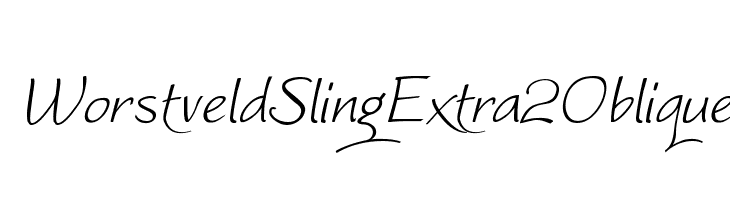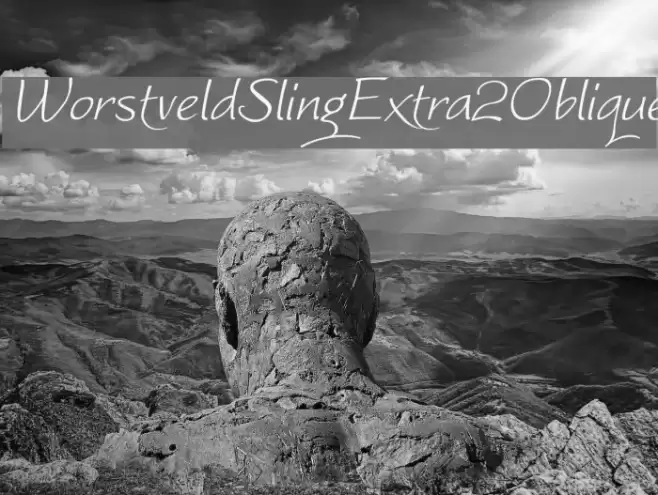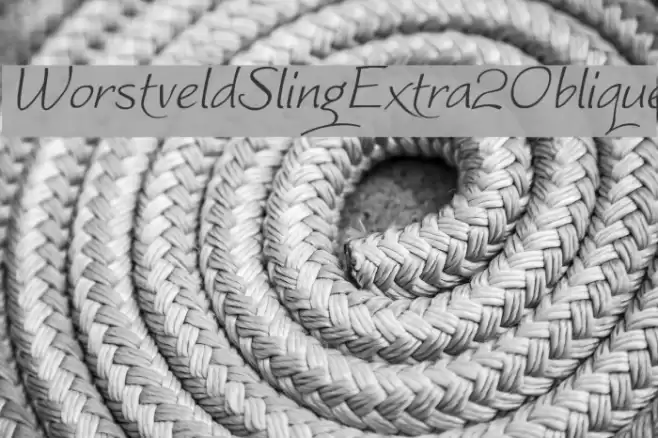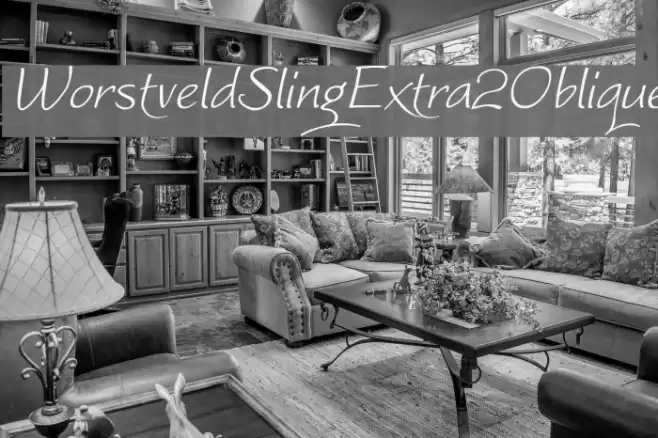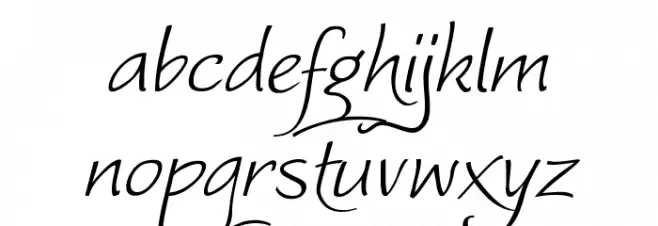
WorstveldSlingExtra2Oblique Font
| Caso de uso | Logos, Invitations, Artistic projects |
| Proyectos propuestos | Ideal for wedding invitations, greeting cards, artistic posters, and branding materials that require a touch of elegance and creativity. |